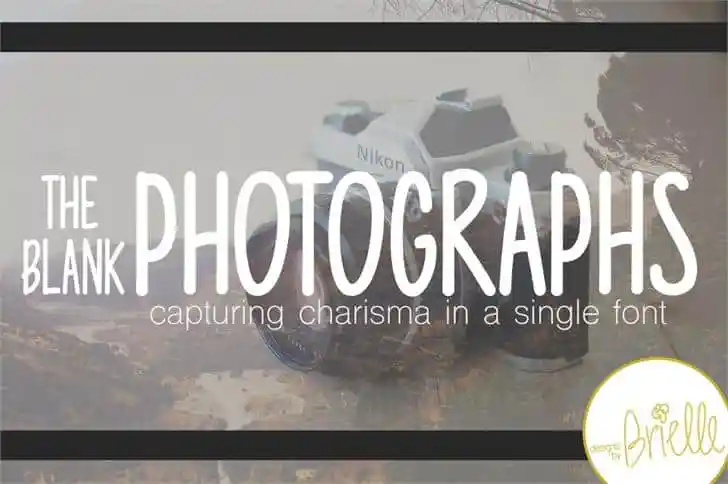
A fonte ‘Photographs’ é uma escolha perfeita para qualquer projeto retrô ou vintage, trazendo ao seu design um toque autêntico e encantador. Desenvolvida por Hamilton, essa fonte se destaca por sua elegância retro que reflete a estética de uma era passada. Ideal tanto para aplicativos digitais quanto impressos, esta fonte carrega o sabor da fotografia em todas as suas linhas elegantes e detalhes cuidadosamente pensados. Suas proporções harmoniosas permitem que você criue texturas suaves e leves, enquanto seu contraste entre a serifada e a sans-serif permite um equilíbrio perfeito. Para usuários de propósitos comerciais, Hamilton oferece uma plataforma online para mais informações sobre as licenças. Seja para design personalizado ou criação de materiais publicitários, ‘Photographs’ se mantém fiel à sua essência enquanto abre portas para inúmeras possibilidades criativas e estilísticas. Com seu design cuidadosamente elaborado por Hamilton, essa fonte atende a todos os requisitos do mundo da comunicação gráfica, combinando com perfeição o encanto de um passado retrô com uma presença moderna.